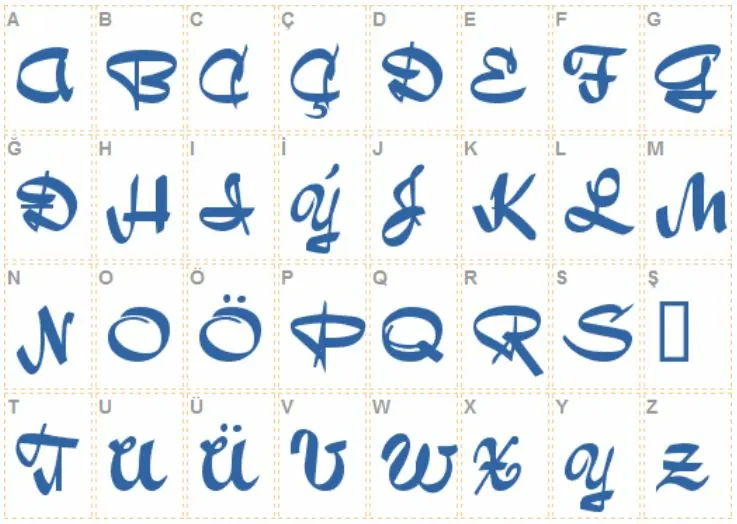
En el artículo de hoy podrás ver una colección de excelentes fuentes tipo lazo para que te descargues gratis y consigas dar calidad a tus trabajos. Se trata de ser original y creativo.
Utilizar una fuente u otra puede mejorar o empeorar un diseño. Por eso es muy importante la tipografía que mejor encaja en ese diseño y ver la integración final de todo el conjunto.
[h2]Pues aquí tienes la colección de fuentes tipo lazo gratis[/h2]
[h3]Ribbons bold[/h3]
Tipografía de lazo negrita.
[h3]Curly Ribbons[/h3]
Tipografía estilo lazo tipo curva.
[h3]Tribbon Font[/h3]
[h3]Fuente estilo lazo: Ribbon of hope font[/h3]
[h3]Tipografías lazo: Ribbon Trim Font[/h3]